孔明先生晚年始终与东吴保持经常性沟通机制,以期巩固双边军事关系,进而使北伐战争朝着以利于既定战略目标发展。正基于上述考量,笔者主张《远涉帖》系亮致瑾函可能性最大,意在向东吴通报出征一路平安,并寄希望在蜀汉北伐期间,字如既往同心协力。故落款未以家书形式作“弟亮顿首”而署“亮顿首”。这是合理的,也是佐证。
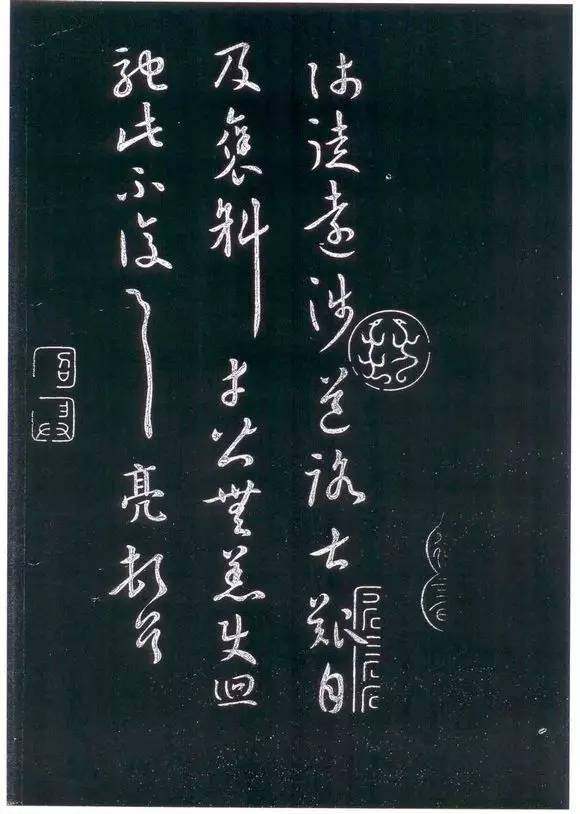
《远涉帖》作为孔明翰墨,自北宋现世后历来被奉若拱璧,《宣和书谱》卷十三《草书叙论》曰:自汉晋宋以还,以草书得名者为多,姑以流传于今者凡得六十五人以其世次之。汉得张芝,蜀得诸葛亮。亮善画,亦喜作草字。虽不以书称,世得其遗迹必珍玩之。今御府所藏草书——《远涉帖》。
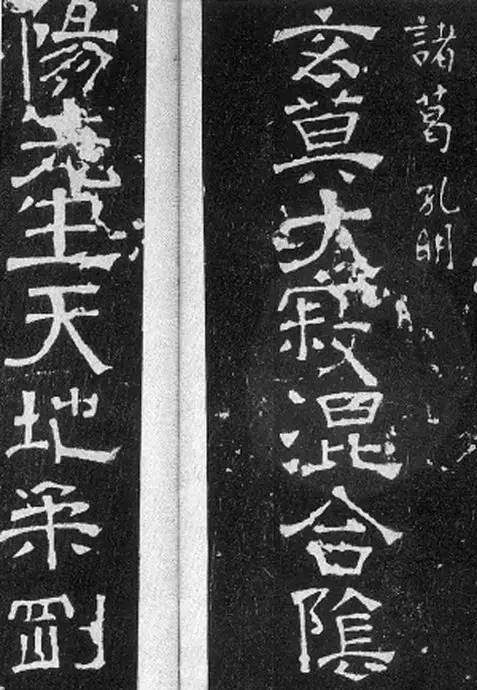
再者,北宋集帖确认为亮书者,尚有大观三年(1109)刊刻《汝帖·玄莫帖》,其帖目明确帖主为诸葛孔明,隶书二行十四字作:玄莫大寂混合阴阳先生天地柔刚。